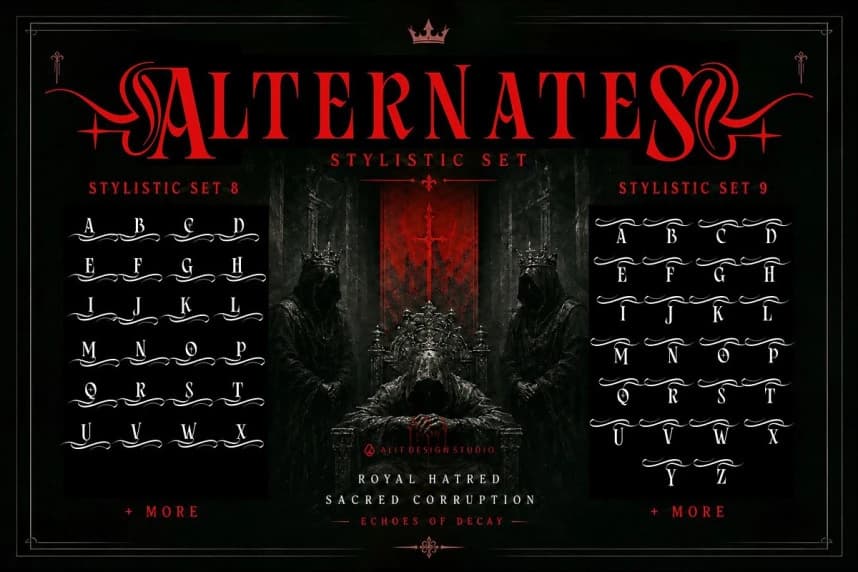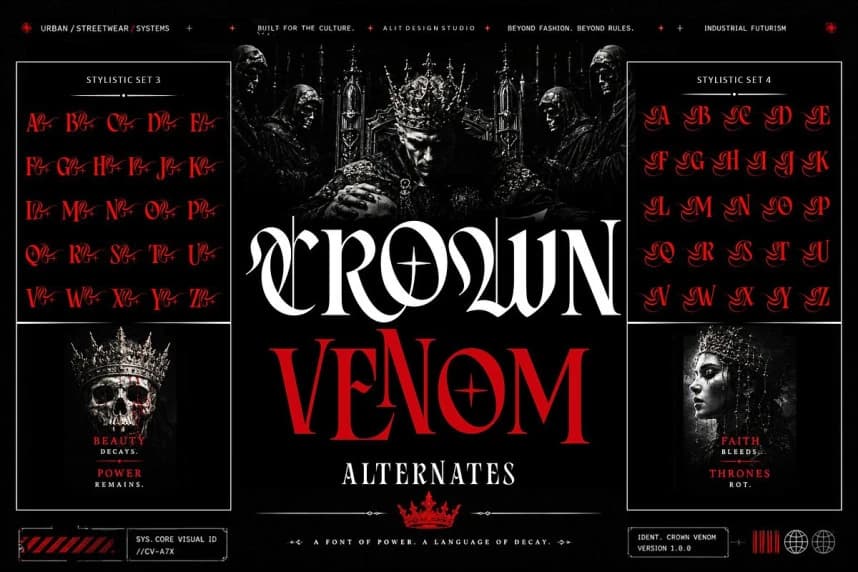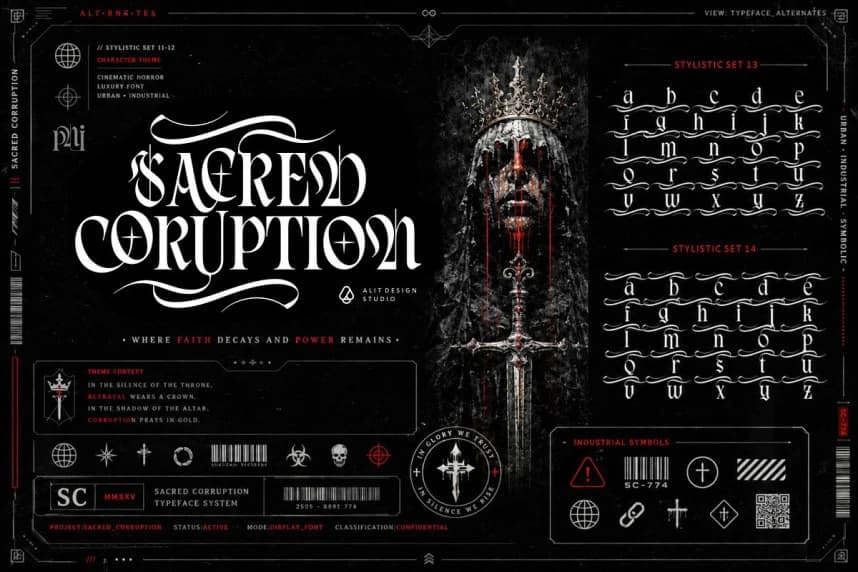
Royal Hatred Font
Royal Hatred Font, karanlık fantezi, kraliyet çürümesi ve kutsal yozlaşmanın estetiğinden doğan özenle tasarlanmış bir gotik serif yazı tipidir. Yüksek etki ve yüksek kontrastlı görseller için tasarlanmıştır. Bu premium yazı tipi, klasik blackletter zarafetini keskin, modern ve neredeyse cyberpunk e
Royal Hatred Font, karanlık fantezi estetiği, kraliyet çürümesi ve kutsal yozlaşmadan doğan özenle tasarlanmış bir gotik serif yazı tipidir. Yüksek etkiye sahip ve yüksek kontrastlı görseller için tasarlanan bu premium yazı tipi, klasik blackletter zarafetini keskin, modern ve neredeyse siberpunk esintili bir saldırganlıkla birleştirir.